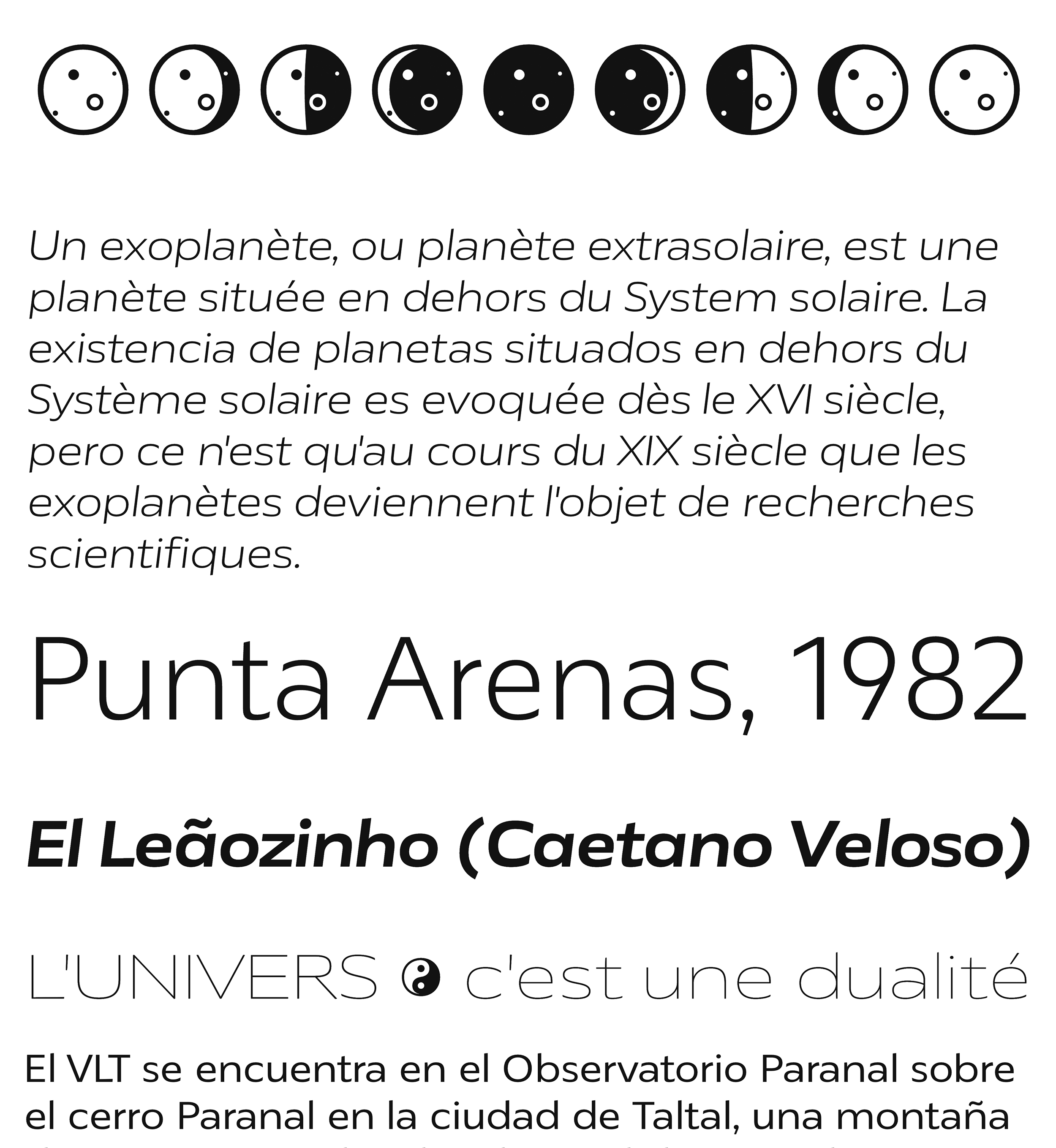
| Descripción | Lira Sans se concibió mediante un método de dibujo racional, lo que permite una forma de letra muy flexible que se adapta a todo el espacio de diseño. Se buscó la claridad y la austeridad en su diseño, sin perder su tono distintivo al componer. Lira se diseñó pensando en la usabilidad para satisfacer las necesidades diarias de la industria gráfica y de la comunicación, especialmente en el diseño de información o editorial, donde la necesidad de una tipografía bien elaborada es crucial. |
| Clasificación | Texto, Títulos, Dingbats |